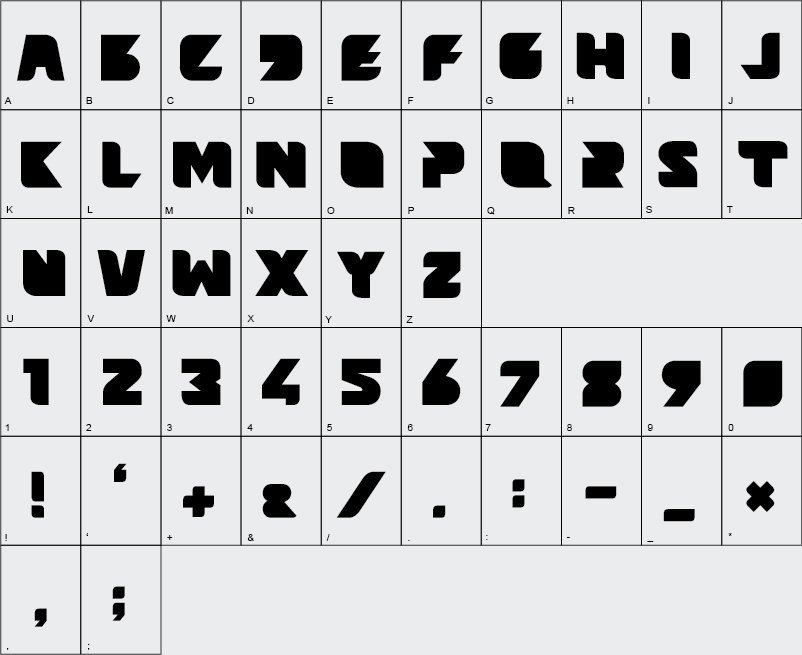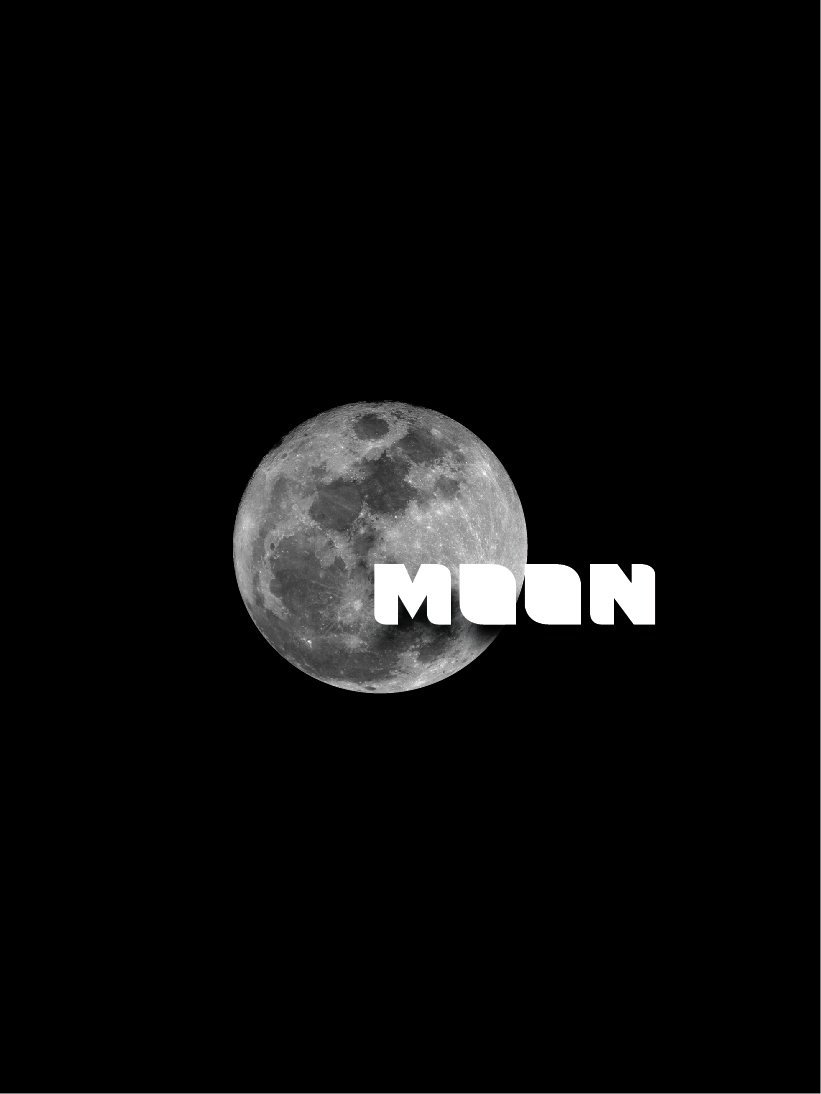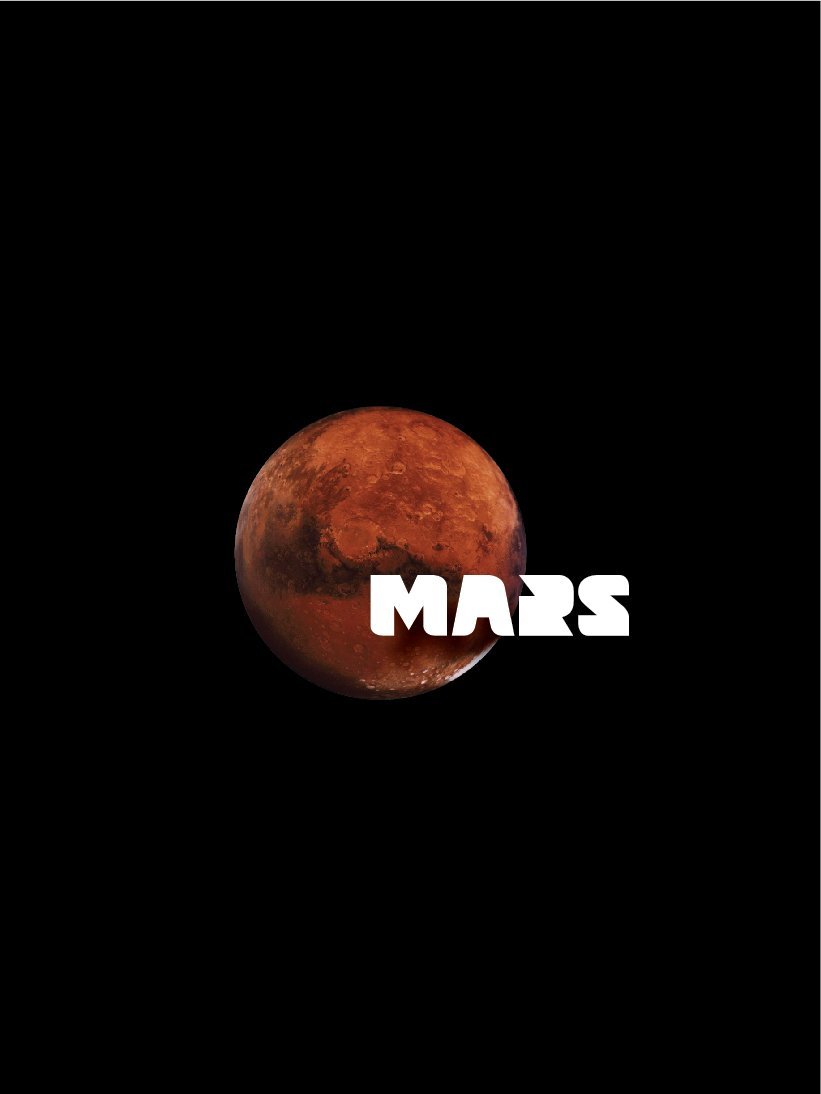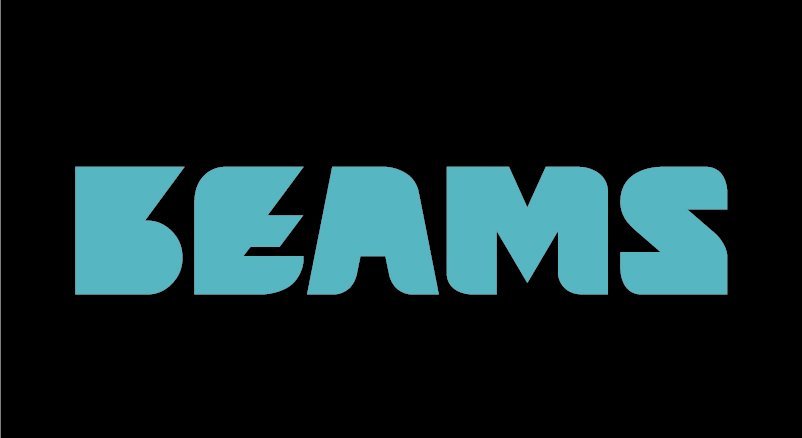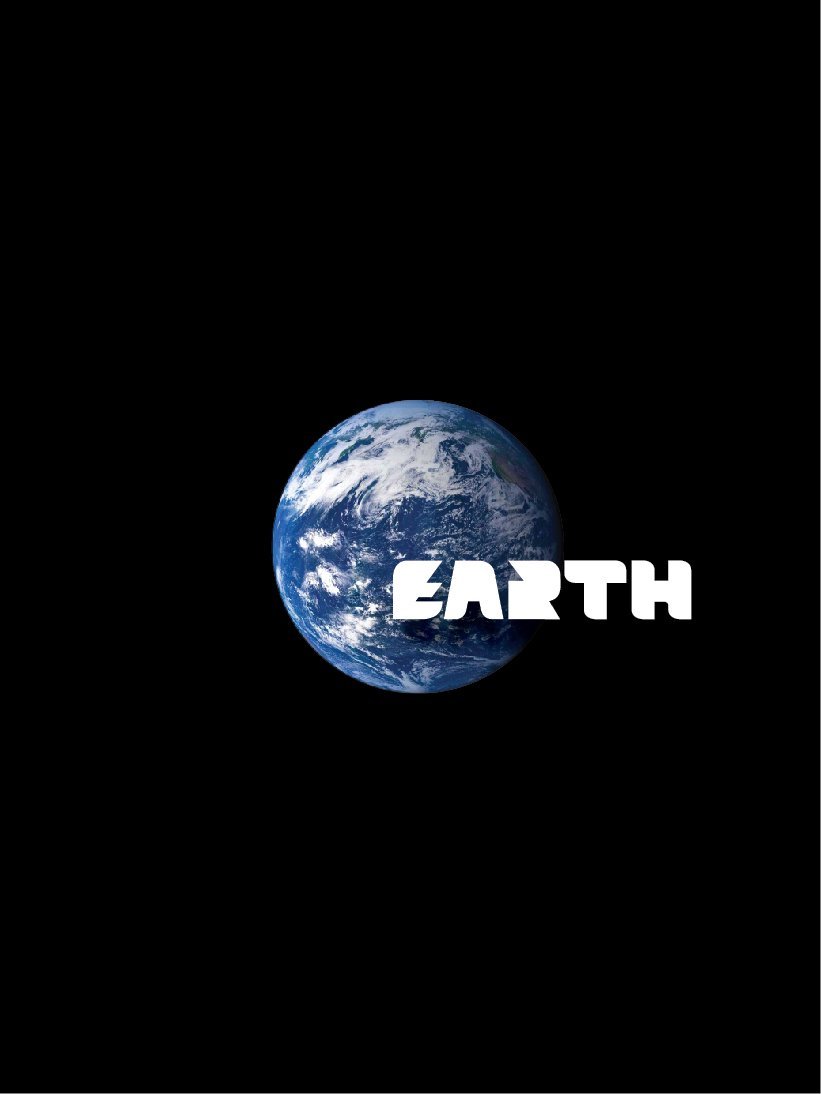
Beams — police futuriste gratuite
Télécharge Beams, une police futuriste pensée pour donner un style moderne et affirmé à tes projets. Elle fonctionne très bien pour les identités visuelles, les affiches, les interfaces web et toute création qui a besoin d’une esthétique nette et contemporaine.
À propos de la police
Beams se distingue par ses formes géométriques et son aspect technique. Elle apporte un caractère fort aux titres, logos et visuels graphiques. C’est une police idéale pour les projets créatifs qui cherchent un style futuriste maîtrisé.
Avantages
- Style moderne avec une personnalité visuelle marquée.
- Lisibilité solide en grand format.
- Utilisable en branding, webdesign, print et motion.